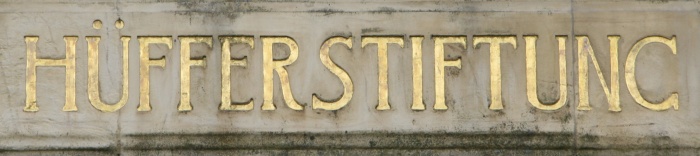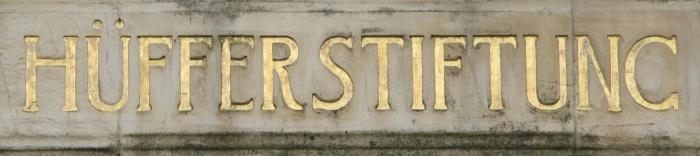
Gebäudebeschriftung um 1900
Ich suche eine Schrift, bzw. viel mehr Informationen zu dieser. Da Sie Anfang des 1900 Jahrhunderts an ein Gebäude angebracht wurde, gehe ich nicht davon aus, dass es sich um eine Satzschrift handelt.
Verwandte Schriften würden mir schon reichen. Habe die Buchstaben teils schon vektorisiert und bei "What-the-Font" nach Verwandten gesucht, doch bin ich mit dem Ergebnis noch nicht recht zufrieden.
Von der Zeit der Erbauung des Gebäudes (1902), der x-Höhe, dem S und R schließe ich auf Jugendstil.. jedoch finde ich keine weiteren Beispiele des wirklich auffälligste Merkmals, dem "G" welches aus der Ferne eher wie ein "C" scheint.
Da das ganze als versenktes Relief in Sandstein gemeißelt wurde, hätte man es  leicht korrigieren können, doch scheint es Absicht zu sein..
Meine Frage ist, ob es andere Schriften mit diesem auffälligen "G" gibt?
... der x-Höhe, ...
Wo siehst du die denn, und was hätte die mit Jugendstil zu tun  :-?
Wozu suchst du ein G, das wie ein C aussieht? Auch, wenn es scheinbar Absicht war, wirkt es doch wie ein Fehler, genauso wie das S ...
Ähnliche Schriften findest du evtl. hier oder hier. Wenn du als Sample Text ein G eingibst, kannst du die Schriften auch gleich daraufhin abchecken.
Wo siehst du die denn, und was hätte die mit Jugendstil zu tun  :-?
Diese »höhergelegte« Mittellänge von H, R, F und E ist schon ziemlich Jugendstil-typisch. Ich denke, das hat strode gemeint.
Stimmt, du hast Recht, die sehe ich gar nicht *g.. Ich meine die Quer- bzw. Haarstriche..
Die Beschriftung der Hüfferstiftung ist Teil einer Seminararbeit bei der ich verschiedene Gebäudebeschriftungen untersuche. Weniger um genau die passende Schrift zu finden.. Viel mehr um um auf Besonderheiten und Details einzugehen und nachdem ich das Internet schon mehrmals auf den Kopf gestellt hab, in der Bibliothek und dem Stadtarchiv auch nicht fündig geworden bin, dachte ich, wende ich mich mal an die Experten.
Mit ein bisschen Fantasie ist die untere Serife des G's auch leicht angeschnitten. Doch da man das von weitem kaum erkennen kann, bzw. die 100+ Jahre Witterung vermutlich auch dazu beitragen haben, hätte man es doch eigentlich mal ausbessern können..
Nun denke ich, dass es die Absicht des Steinmetz war.. Aber warum? (..werden wir wohl nie erfahren..) bzw. wäre es schön irgendwo einen Vergleiche zu sehen.. Also nur einen des G's.
Soviel ich auf der Abbildung erkennen kann, ist dies keine Steinmetzarbeit, sondern in Stuck-Technik gearbeitet.
Stuckmörtel verwittert innerhalb einer längeren Zeitspanne und wurde wahrscheinlich mehr als einmal restauriert. Ob dies immer von Profis durchgeführt wurde, bezweifle ich. Von dem Originalschriftzug ist dann nur noch diese Variante mit dem eigenartigen „G“ geblieben.
Das „G“ in dieser Form ist kaum die Absicht des Schriftgestalters gewesen.